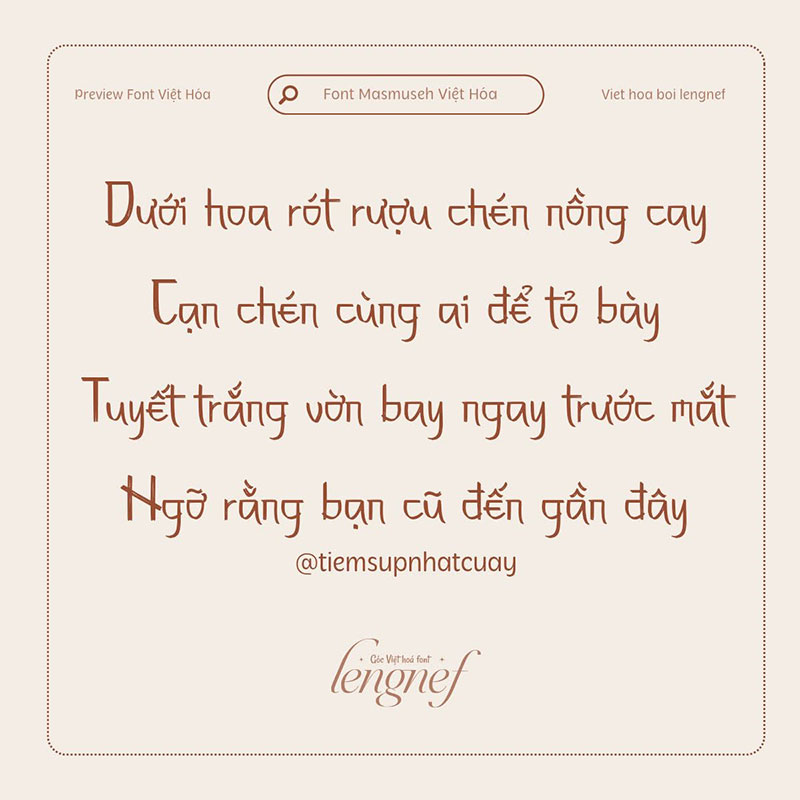
Share Font 69 || LF Masmuseh
• Tác giả: Allouse Studio
• Việt hóa: lengnef
Font LF Masmuseh Việt hóa
Masmuseh là một phông chữ viết tay, cảm giác đậm chất Nhật Bản. Masmuseh rất phù hợp cho mọi tiêu đề, logo, bao bì sản phẩm, xây dựng thương hiệu, tạp chí, mạng xã hội, đám cưới, hoặc đơn giản chỉ để thể hiện chữ trên nền.